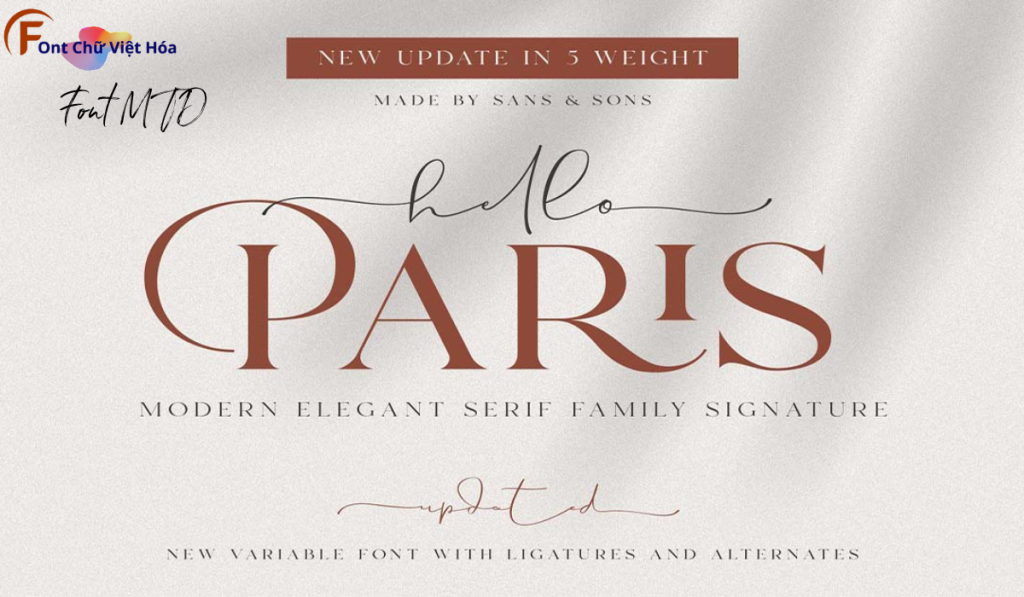
Font MTD Hello Paris Việt Hóa
Phân loại: cá tính, độc đáo
Kiểu chữ: có chân
Font MTD Hello Paris Việt Hóa, thuộc bộ font MTD, mang phong cách hiện đại và sáng tạo, phù hợp cho các dự án thiết kế như poster, logo, và bao bì sản phẩm. Với các nét chữ không chân và độ dày đều đặn, Font MTD Hello Paris Việt Hóa không chỉ dễ đọc mà còn tạo cảm giác hiện đại và phá cách. Việc Việt hóa font giúp người dùng dễ dàng tích hợp vào các thiết kế tiếng Việt, mang lại sự tiện lợi và nâng cao tính thẩm mỹ.